タイポグラフィはんこ「TYPO(タイポ)」
義務を遊びにするイラスト入りはんこ「ずかんシリーズ」を展開するインターネットのはんこSHOP「印鑑はんこSHOPハンコズ」を運営する岡田商会から、図形と文字の美しさが融合した新しいコンセプトのデザインはんこ「TYPO(タイポ)」が2月1日(金)より専用サイトにて販売を開始した。
タイポグラフィはんこ「TYPO(タイポ)」は、タイポグラフィ(活字デザイン)の要素を取り入れたオーダーメイドのはんこで、タイポグラフィのデザインを生かした個性的なハンコを作りたいという想いから生まれたオリジナルのはんこになっている。
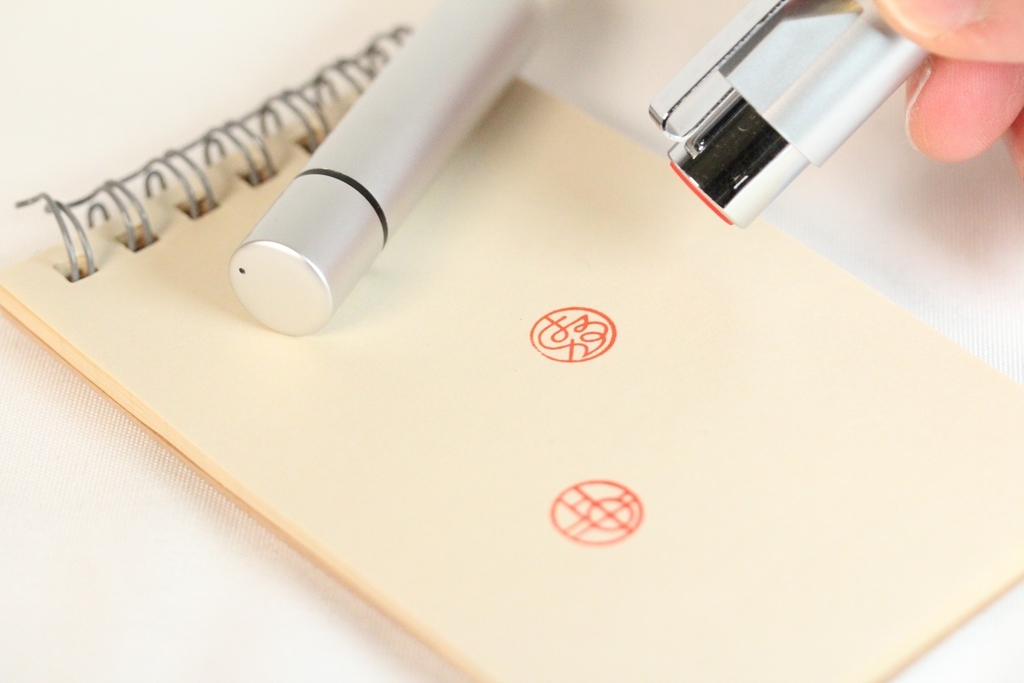
デザインは、幾何学模様をデザインに取り入れた曲線的で柔らかな印象の「Geometry(ジオメトリー)」とシンボリックな記号を取り入れた直線的でモダンな印象の「Symbol(シンボル)」の2種類から選択できる。
いずれも申し込んだ名前をもとに専属のデザイナーが1つずつデザインを制作していく。
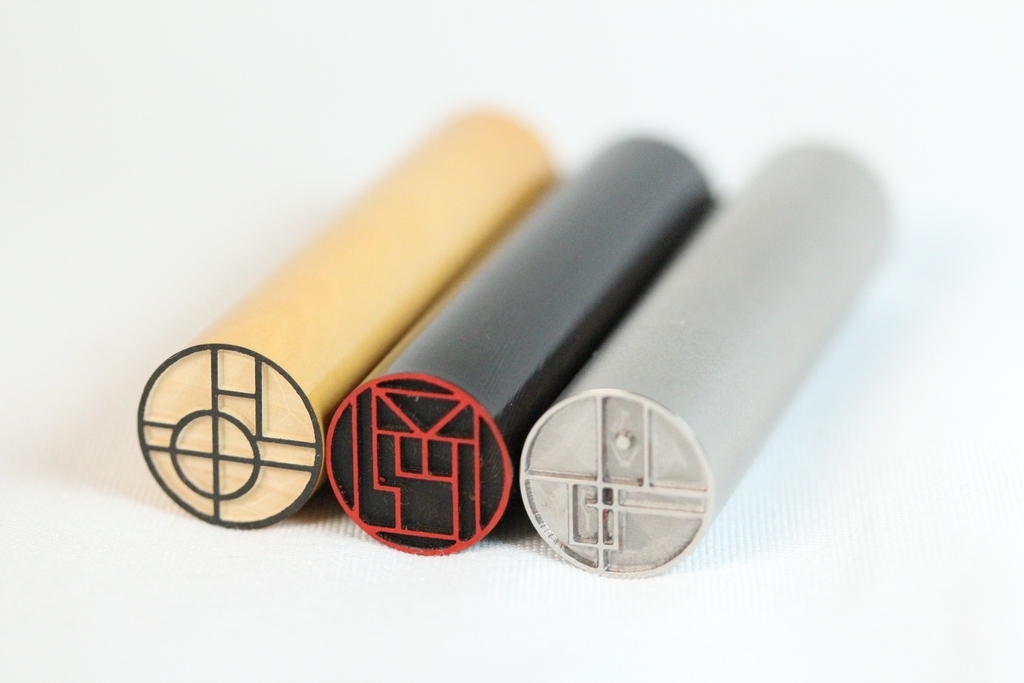
ユニークで個性的なものや、他の人とは違うものをお探しの方にぴったりのはんこになっている。
さらにTYPOは、漢字はもちろん、ひらがな・カタカナ・アルファベットの名前にも対応。
▼「上田」「岡山」「佐々木」「ヒカル」「はるか」などいろんな名前で制作した見本(上段がGeometry(ジオメトリー)で下段がSymbol(シンボル)の制作サンプル)。
たとえ画数の少ないシンプルな名前であっても、専属のデザイナーがタイポグラフィの要素を取り入れたユニークなデザインに制作する。
役所によっては実印として使うこともできる、タイポグラフィはんこ「TYPO」。まるで自分だけのロゴマークのようなデザインでできあがるハンコは、自分の名前ならどんなデザインになるか想像しながら到着を待つのも楽しみの1つ。
ロゴマークみたいなタイポグラフィはんこ「TYPO」風なハンコを自分でも作ってみた
ネットで検索した2019年2月8日現在、トレンドになっていそうな名前でロゴマークみたいなタイポグラフィはんこ「TYPO」風なハンコを自分でも作ってみた。
タイポグラフィはんこ「TYPO」風なゴーン
タイポグラフィはんこ「TYPO」風な新井
タイポグラフィはんこ「TYPO」風な朴
タイポグラフィはんこ「TYPO」風な辻元
タイポグラフィはんこ「TYPO」風な大坂
タイポグラフィはんこ「TYPO」風な小室